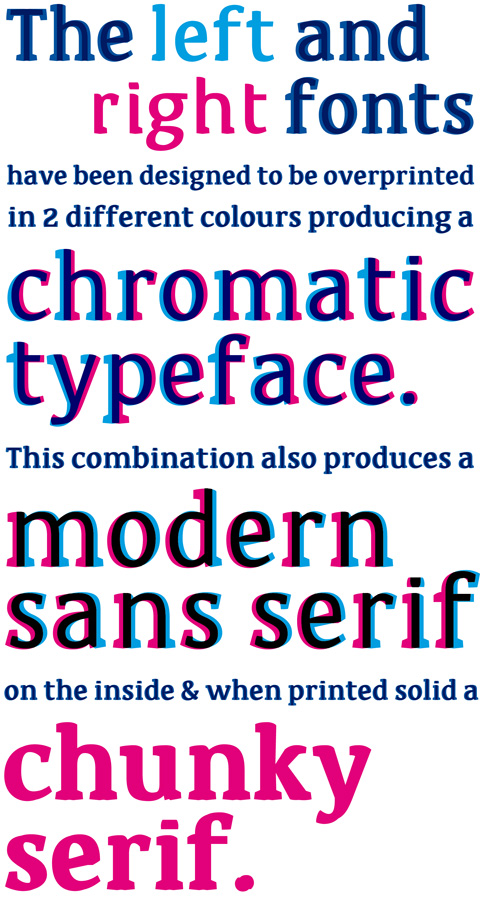
4 tipografias en dos
Este proyecto desarrollado por Daniel Rhatigan consisten en dos tipografias semi serifs, en version izquierda y derecha,que al superponerse con solores solidos nos crean una tipogrfia estilo serif, y cuando se mezclan en colores diferentes nos dan como resultado un tipo san serif humanista, un asunto muy astuto, y para bien el articulo pasenle aca y para checar mas trabajo del señor Rhatigan, es por aqui.